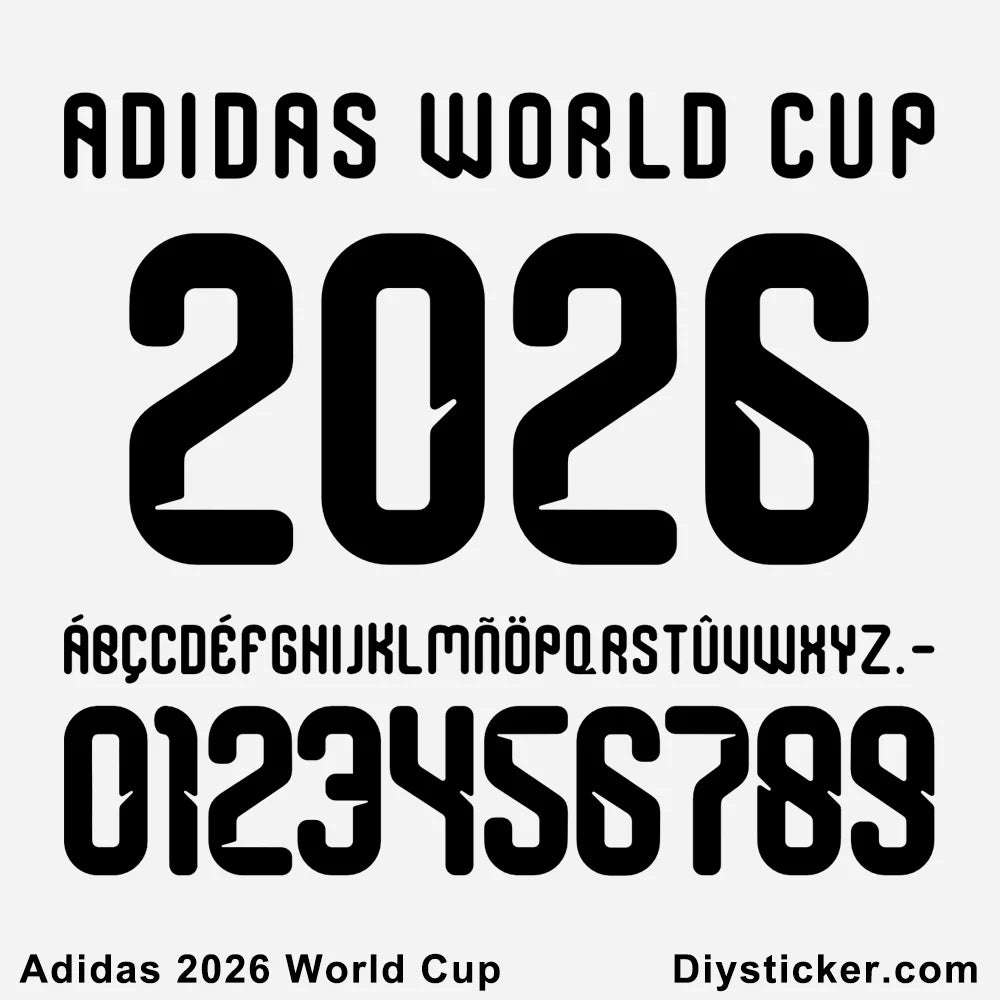
TIPOGRAFIA ADIDAS MUNDIAL 2026
TIPOGRAFIA  SIN LOGO VECTORIZADA IDEAL PARA ESTAMPAR UNIFORMES Y REALIZAR DISEÑOS
TIPOGRAFIA PARA TODAS LAS SELECCIONES QUE VISTE LA MARCA